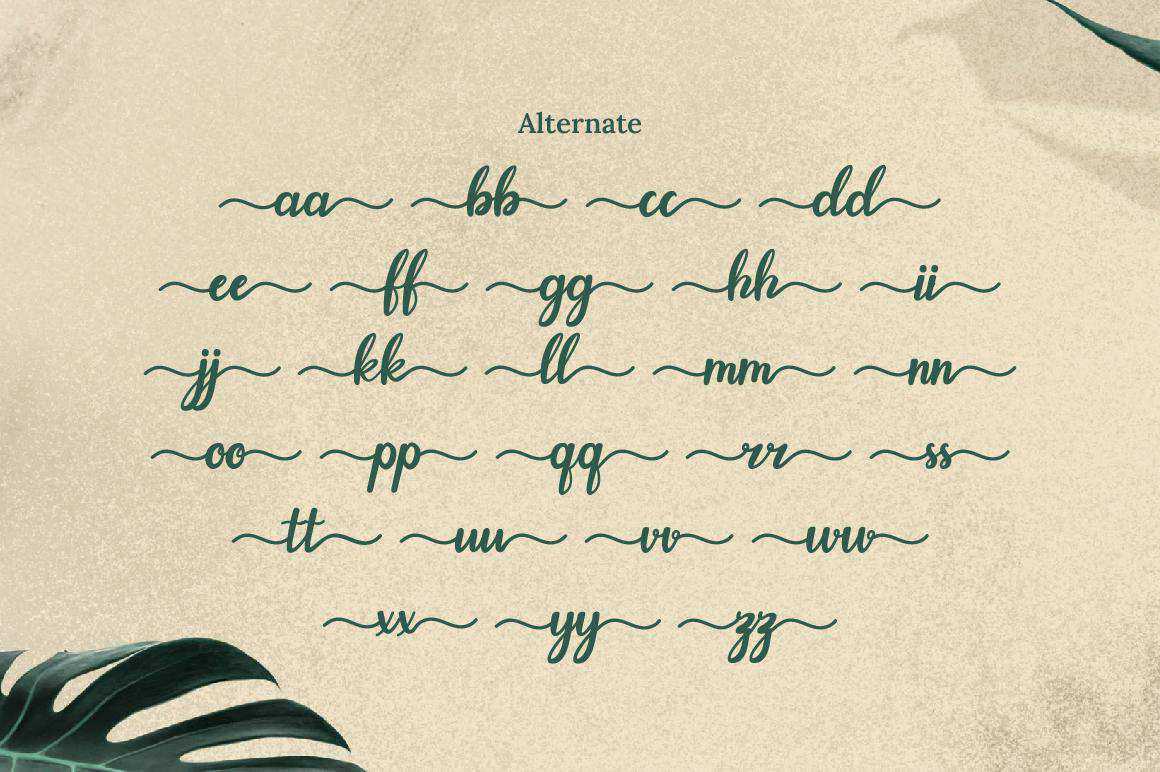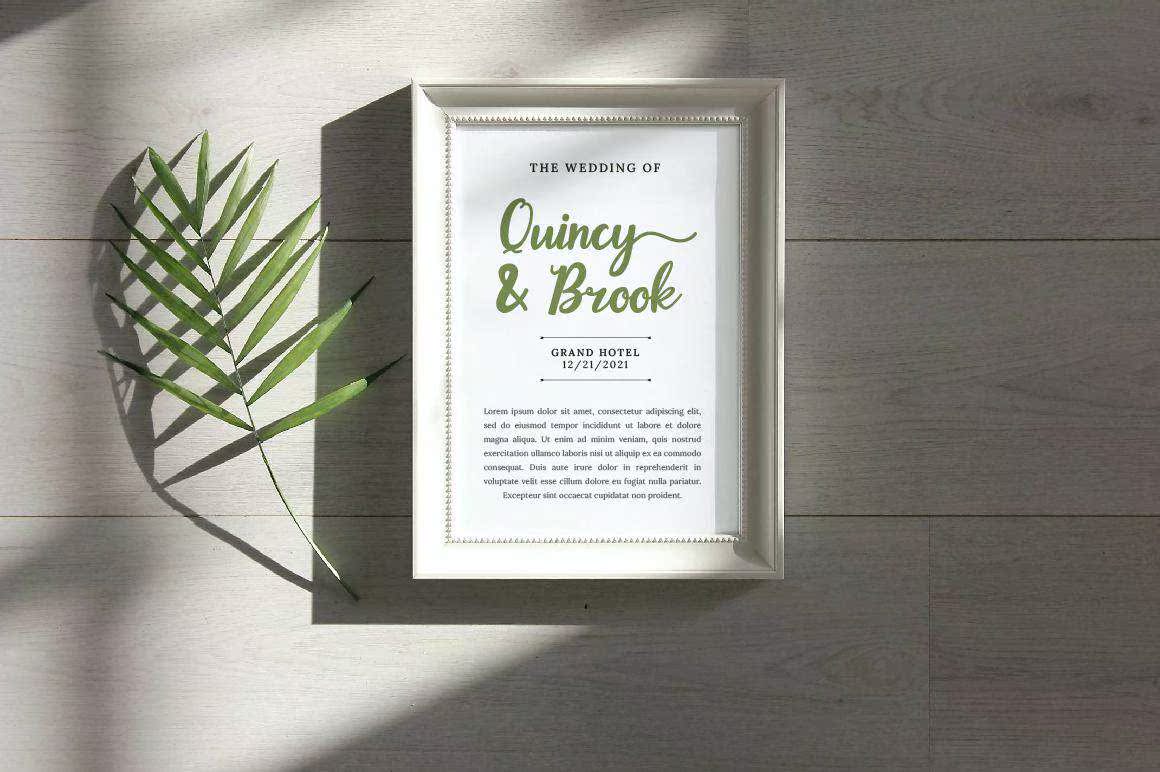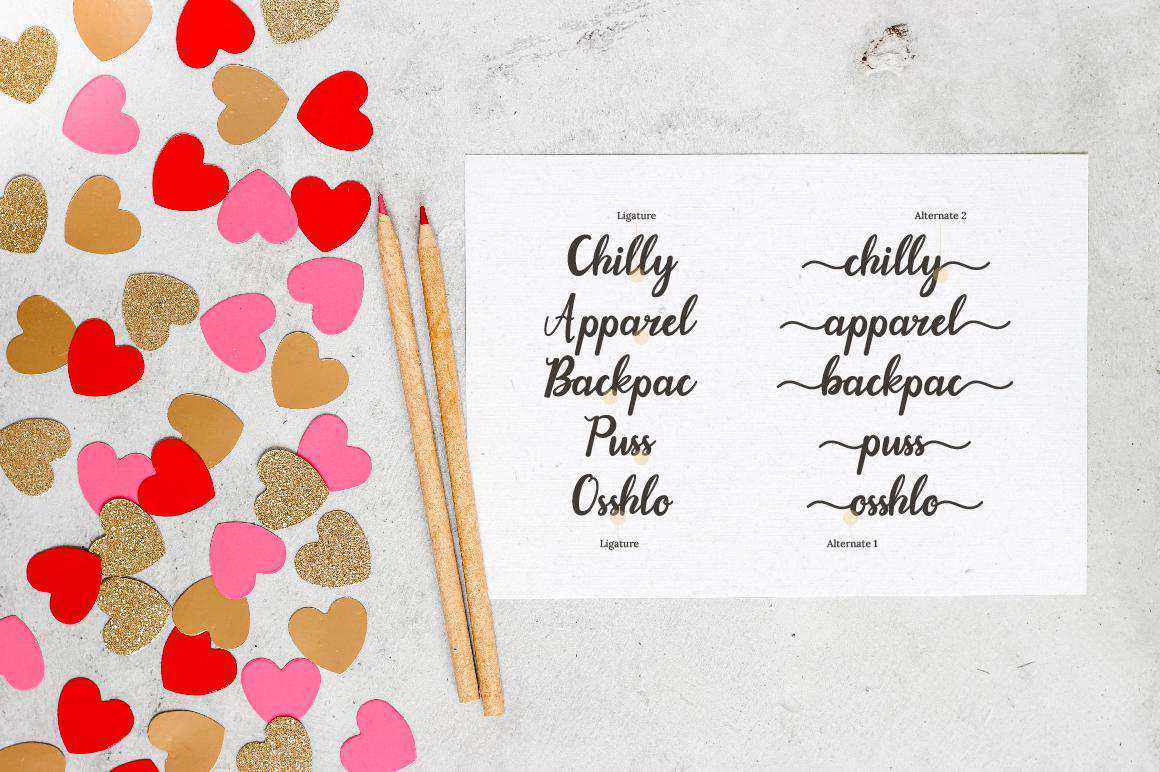
欢迎光临,Evergarden!Abeautifulfontscript!这款字体非常适合女性和女孩主题的项目!您可以使用Ligatures和Style Alternative创建自己的自定义文字。添加您最具创造性的想法,并注意如何让MCome充满活力!欢迎光临,Evergarden!Abeautifulfontscript!这款字体非常适合女性和女孩主题的项目!您可以使用Ligatures和Style Alternative创建自己的自定义文字。添加您最具创造性的想法,并注意如何让MCome充满活力!